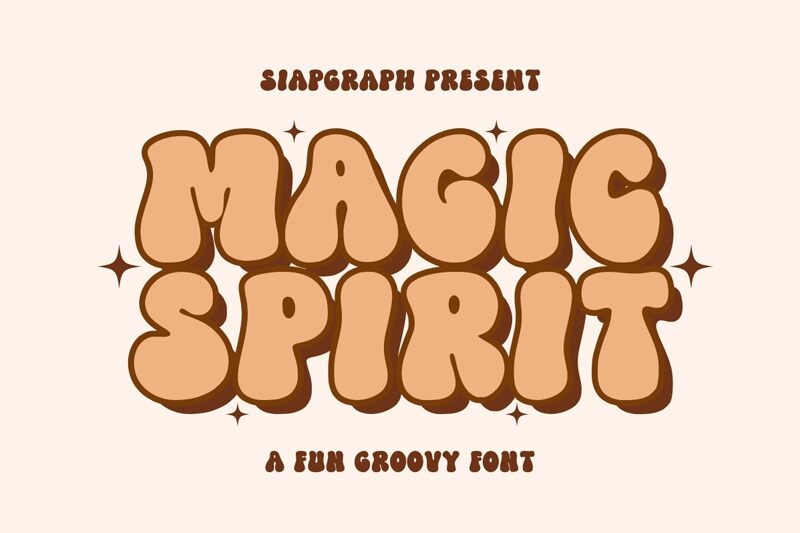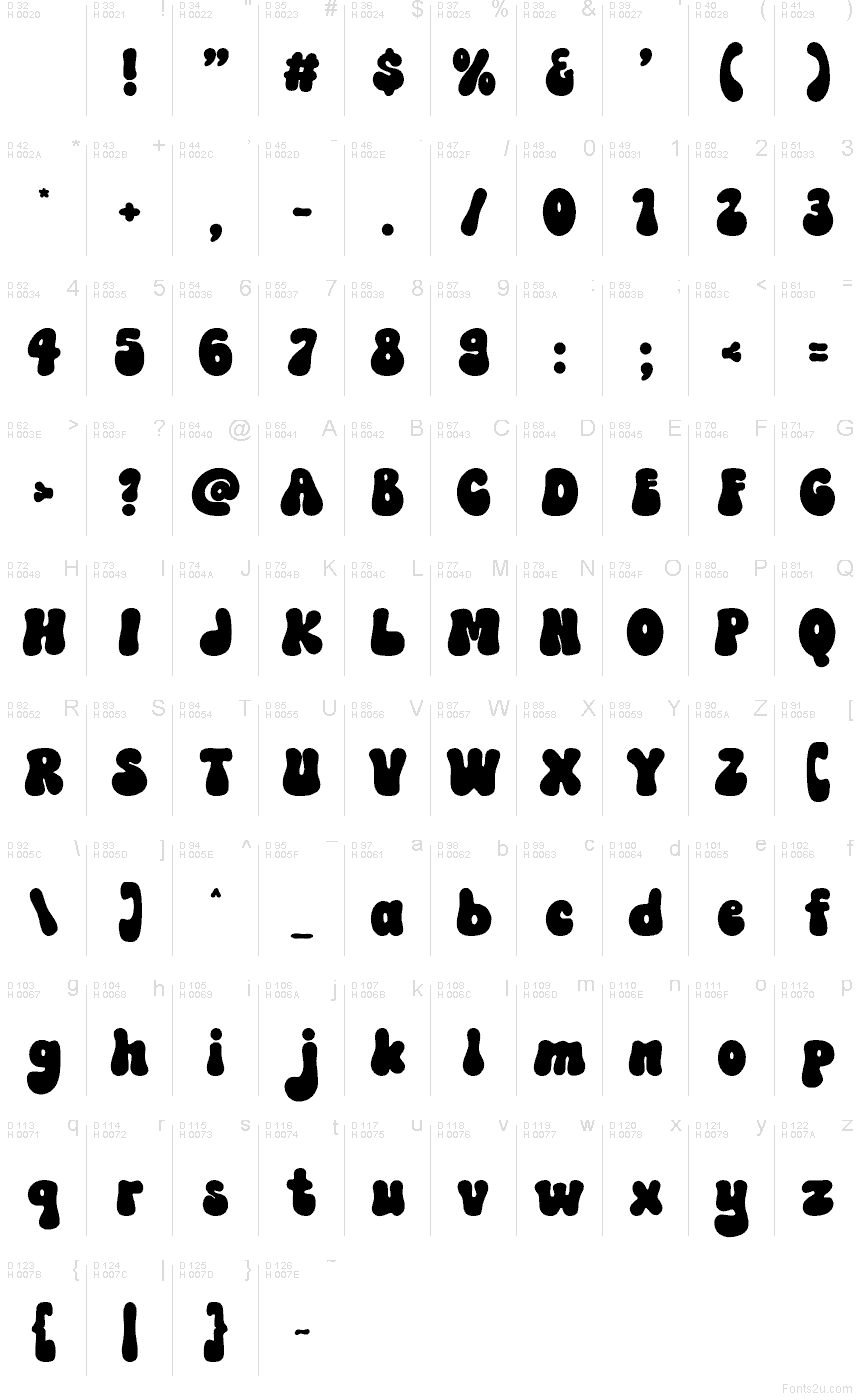
Magic Spirit Regular
Magic Spirit od SIAPGRAPH STUDIO je bezplatné, groovy písmo, ktoré tvoria bacuľaté, zaoblené tvary a pomalá, vlnitá silueta pripomínajúca plagáty zo 70. rokov. Písmená pôsobia mäkko a ľahko vláčne, namiesto geometrickej strohosti, čo dodáva dizajnu uvoľnený rytmus evokujúci pohyb lávovej lampy.
Tento charakter robí z Magic Spirit prirodzenú voľbu pre obaly albumov, festivalové plagáty, vintage obaly, branding kaviarní a výraznú grafiku na sociálne siete, kde hlavnú pozornosť púta práve tvar písma. Skvelo vynikne v krátkych nadpisoch a logách, najmä ak hľadáte teplý, psychodelický nádych namiesto neutrálneho blokového písma.